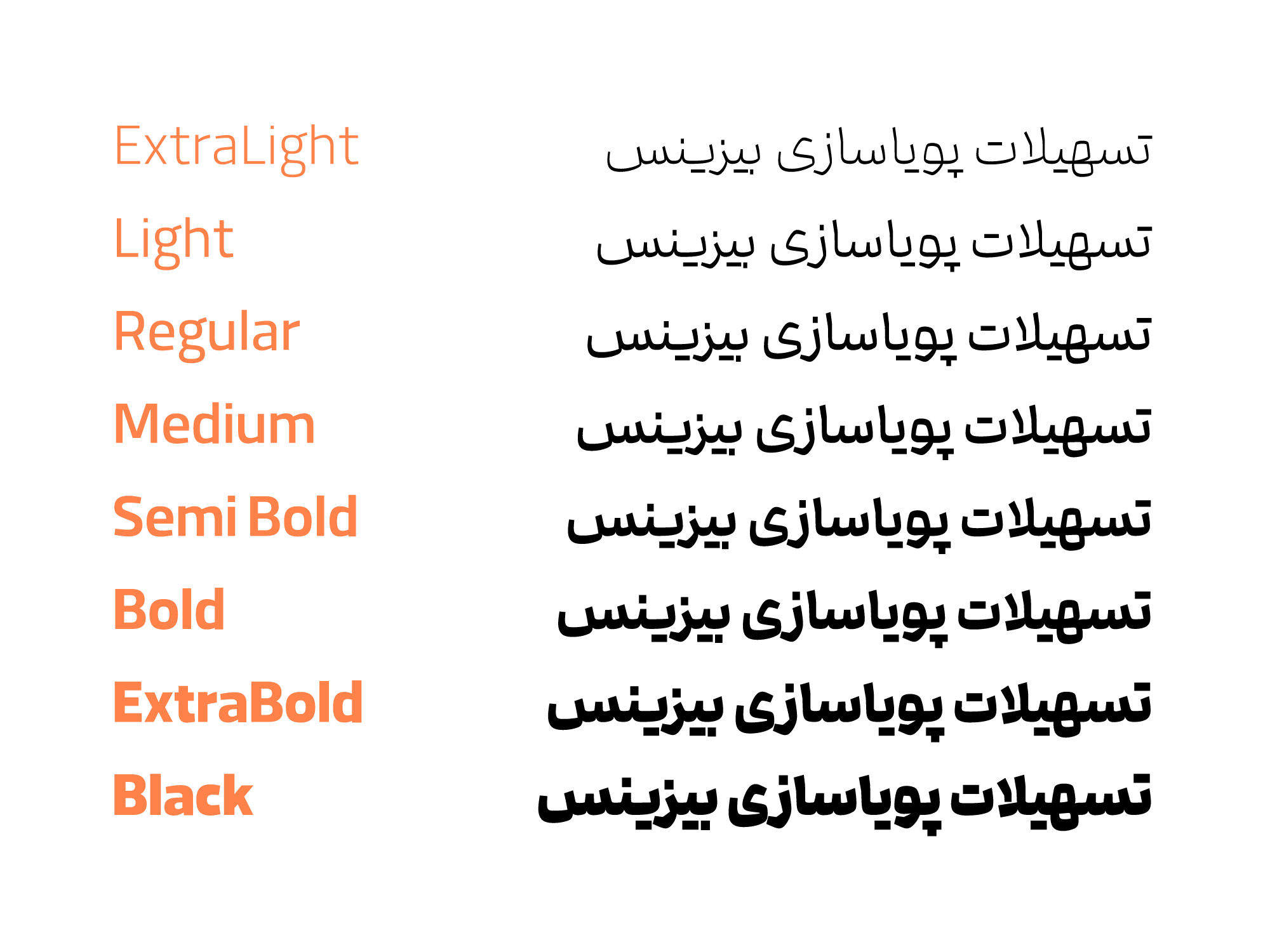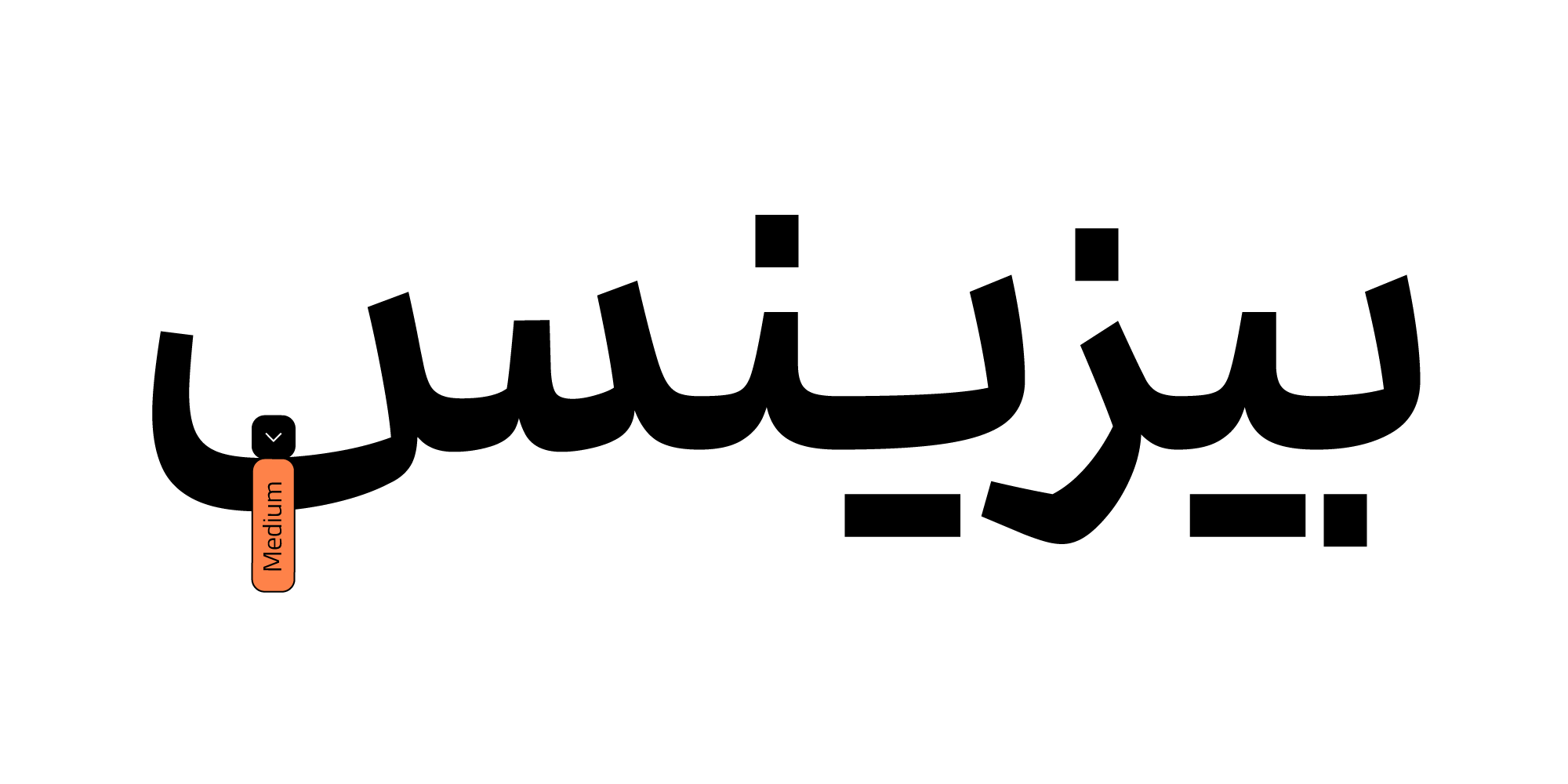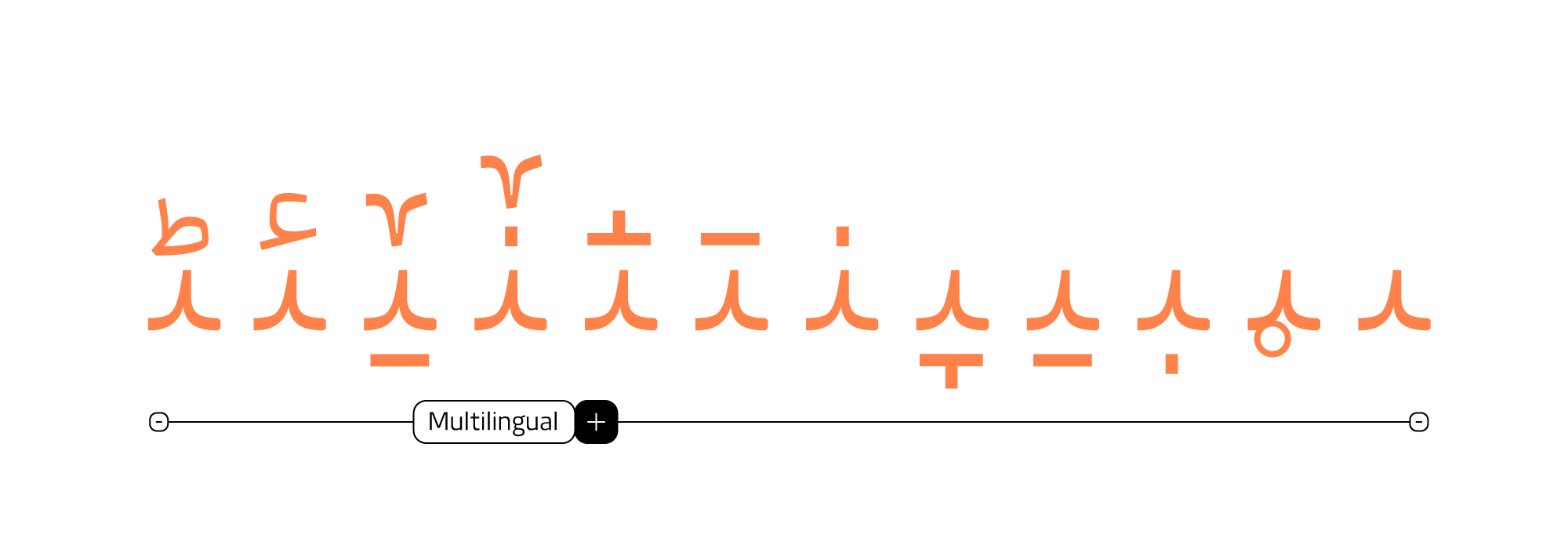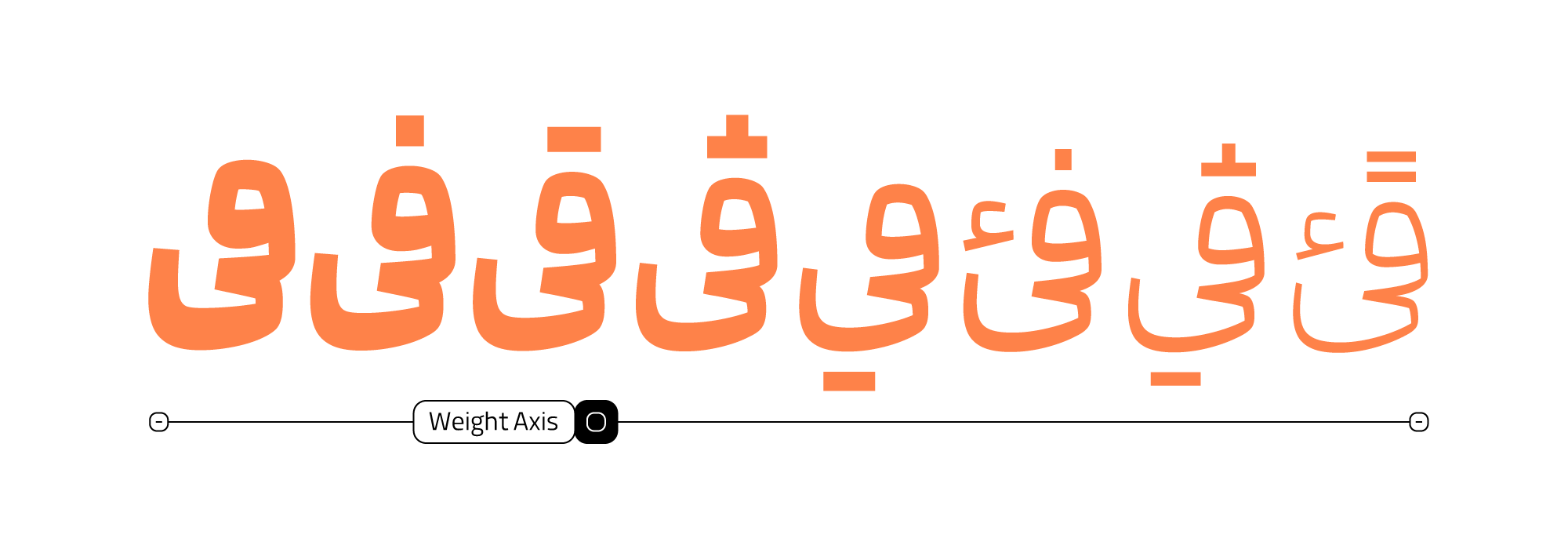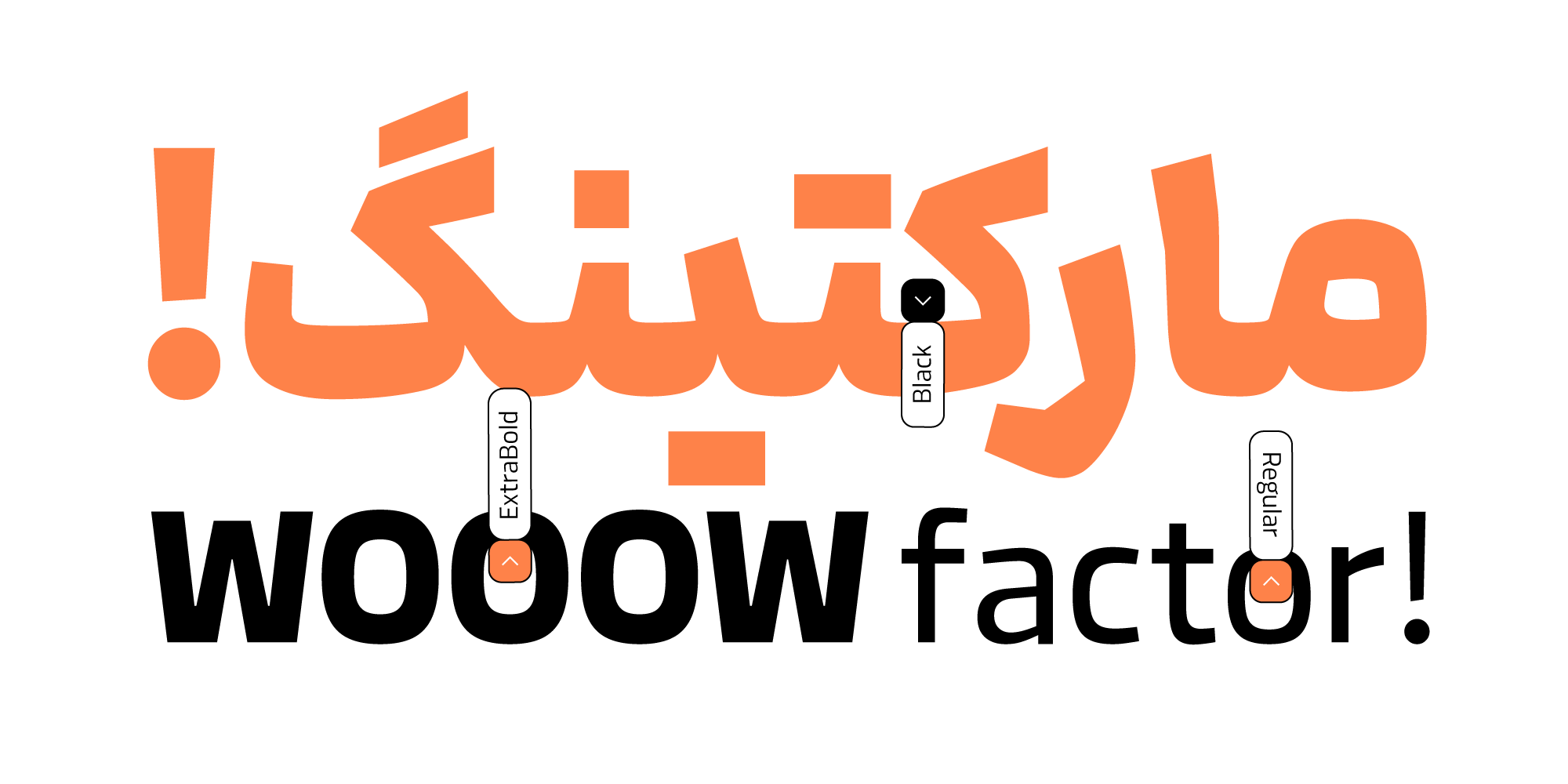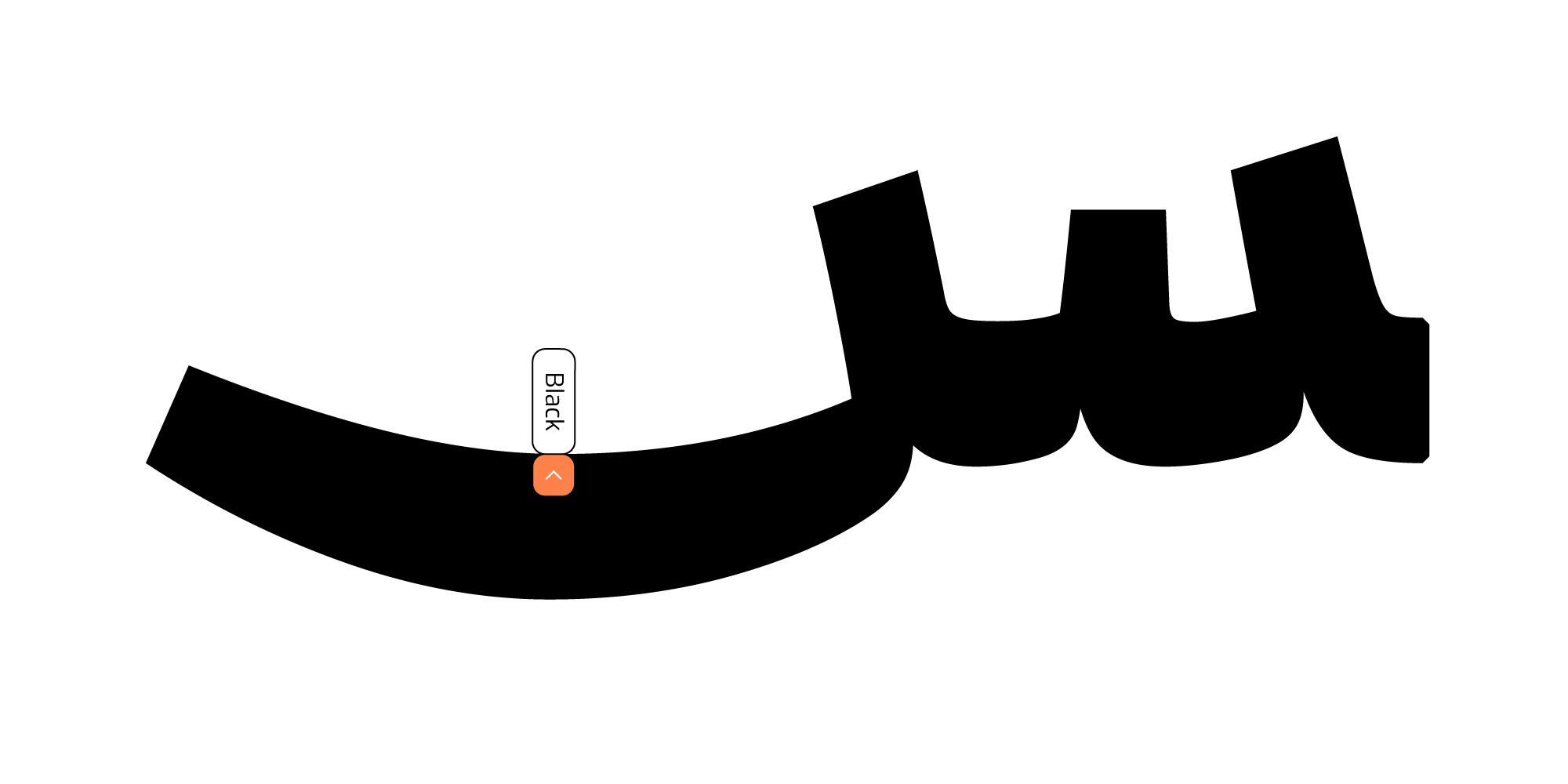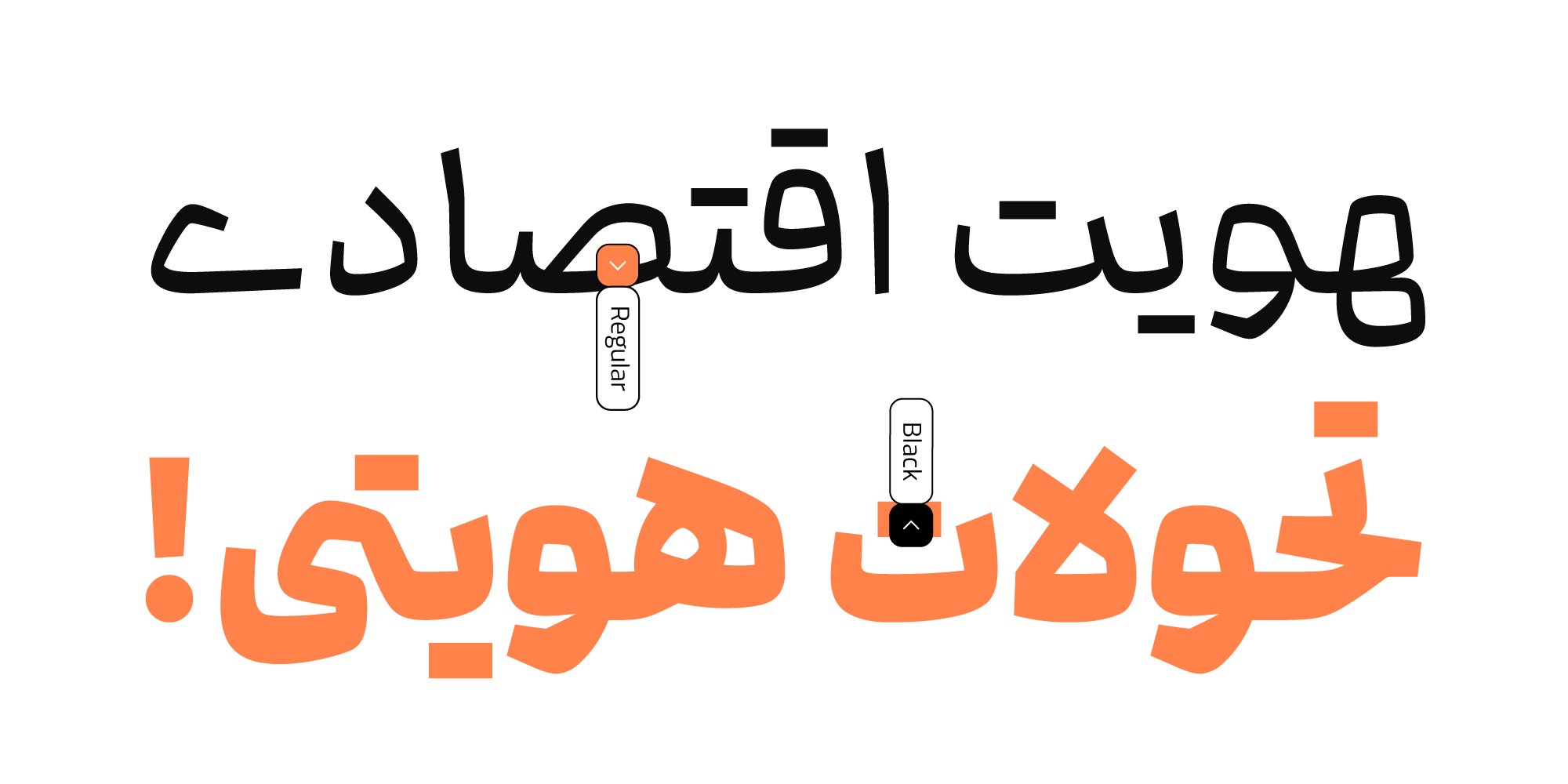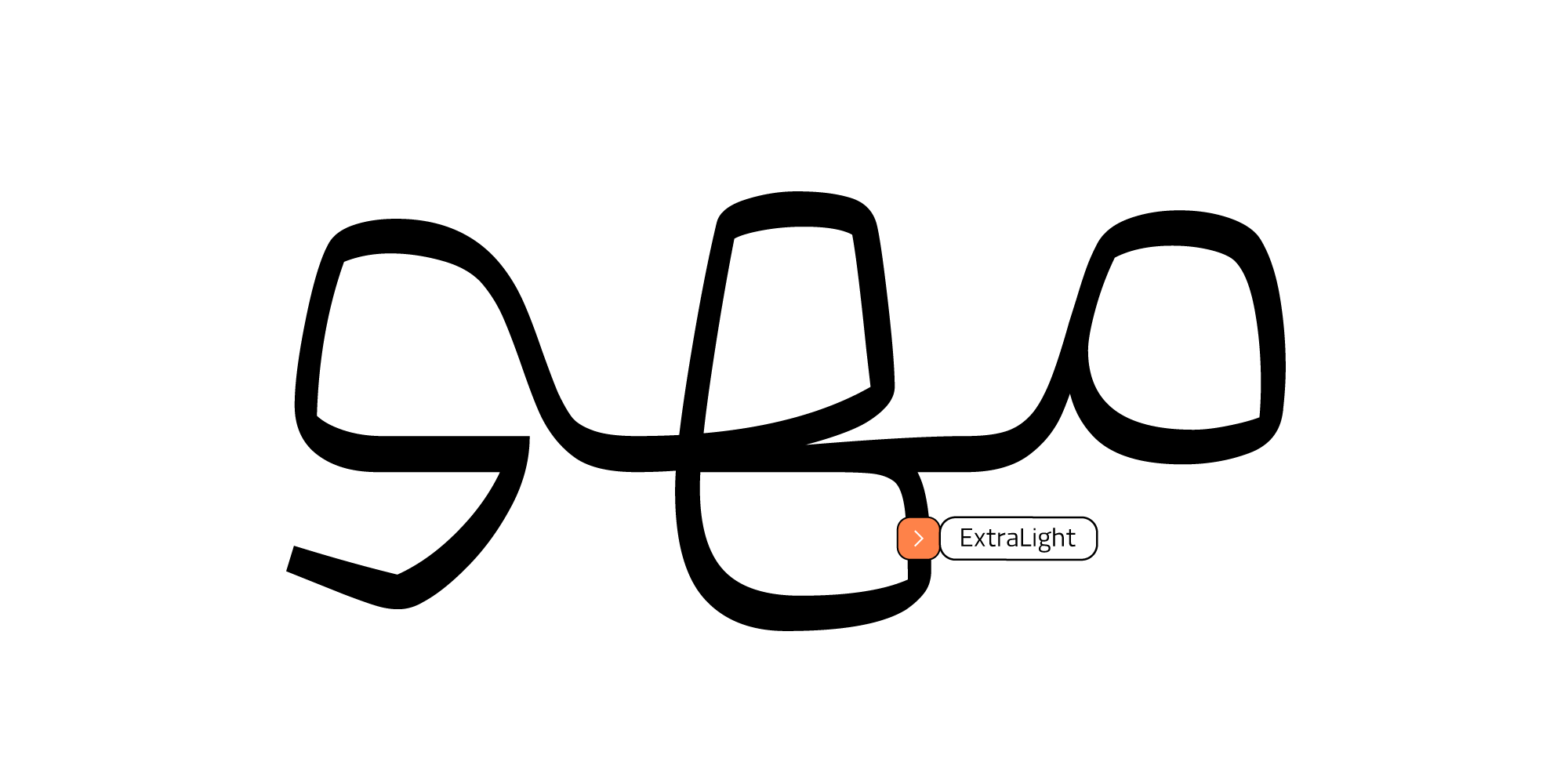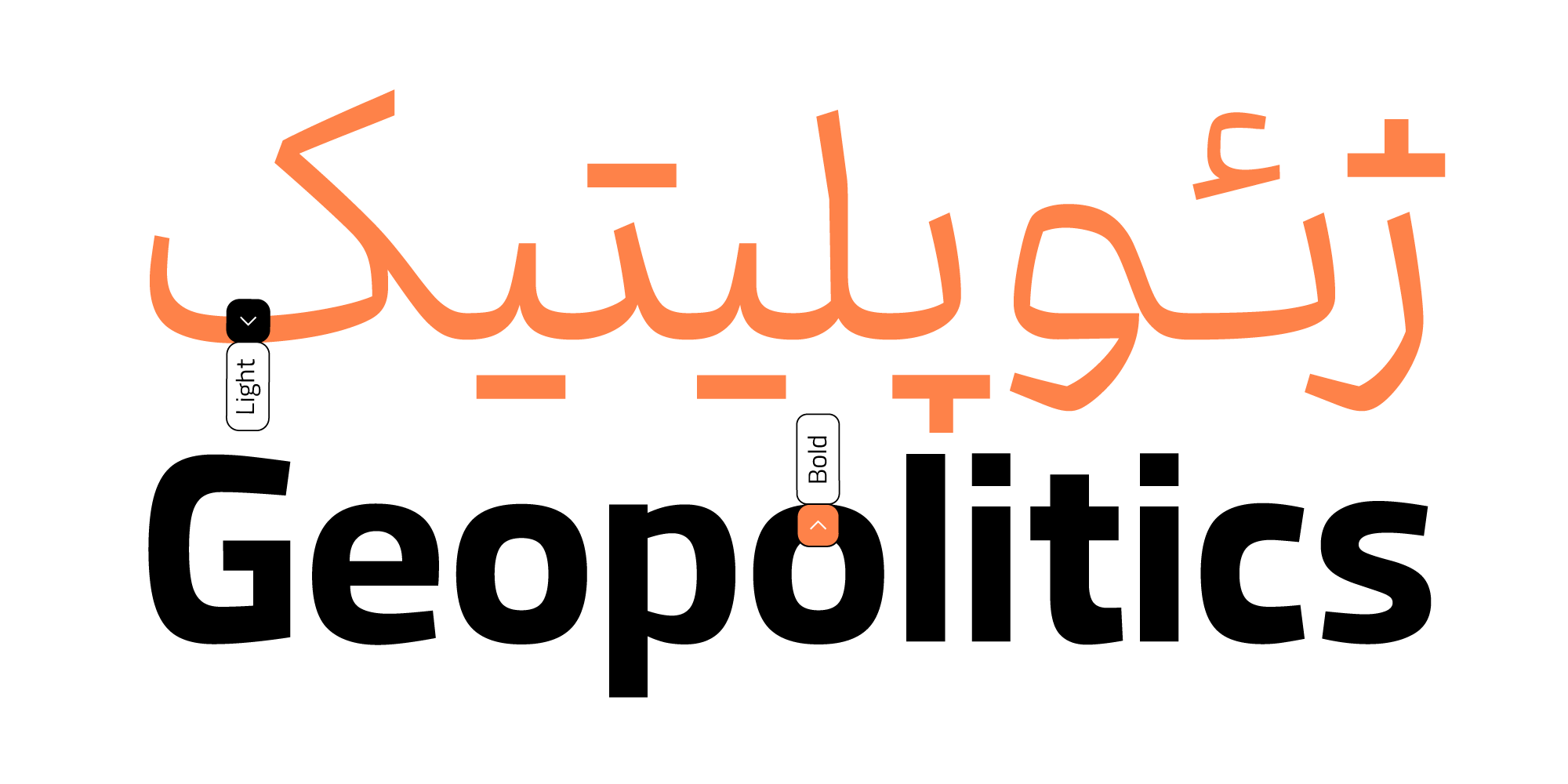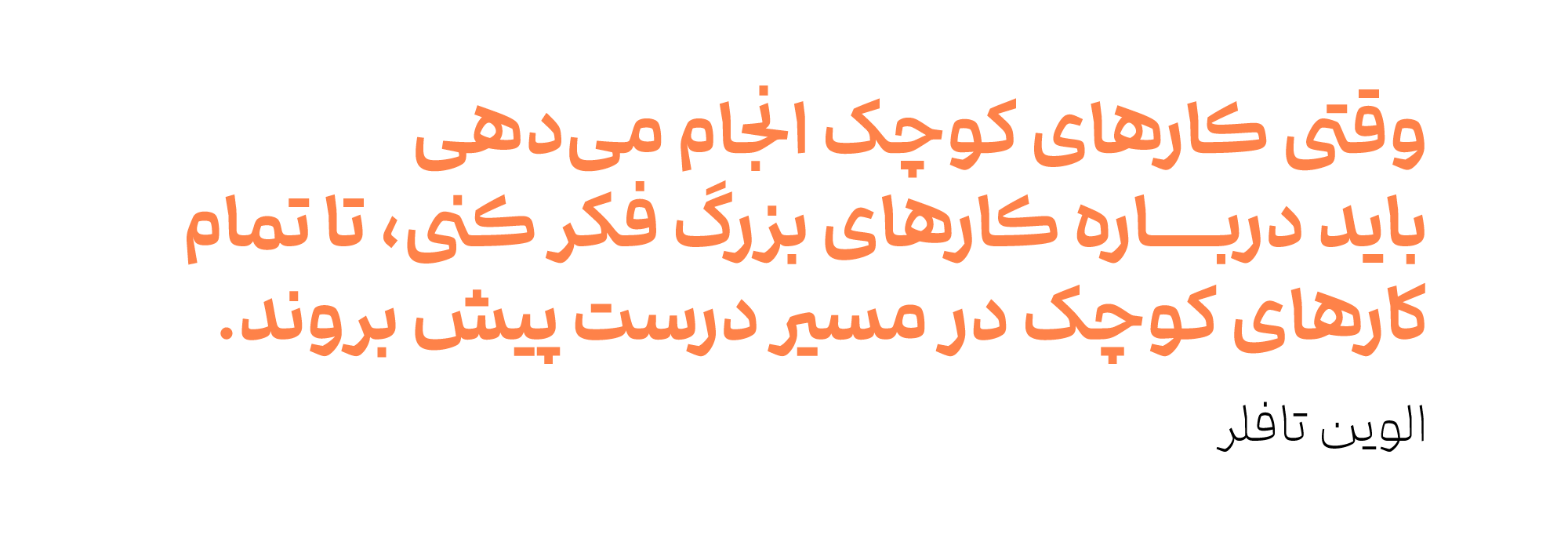
در پی یافتن تناسباتی جدید با حفظ ویژگیهای پایهای رسمالخط فارسی، اولین اتودهای فونت درباره در سال ۱۴۰۱ شکل گرفت. به مرور تناسبات و ویژگیها تغییر یافتند تا اوایل سال ۱۴۰۴ که وزن اکسترالایت کامل شد و سپس مابقی وزنها طراحی شدند.
وریبل فونت
فونت «درباره» به صورت وریبلفونت ارایه شده است که علاوه بر ایجاد دسترسی به وزنهای میانی بین وزنهای استاندارد، تمام وزنها در قالب یک فایل فونت را در دسترس قرار میدهد.
وزنهای استاندارد
«درباره» در بسته حرفهای خود، ۸ وزن استاندارد از ExtraLight تا Black را دارد که این فونت را برای کاربردهای متنوع از تولید محتوی فضای مجازی و UX/UI گرفته تا تبلیغات و چاپ مناسب میسازد. خانواده فونت «درباره» برای استفاده در فضاهای وب نیز بهینهسازی شده است و فایلهای مورد نیاز در کنار فایلهای اصلی قرار داده شده است.
پشتیبانی از زبانهای انگلیسی، عربی، کردی و اردو
تایپفیس «درباره» برای زبان فارسی طراحی شده است و زبانهای عربی، کوردی و اردو و انگلیسی را نیز پشتیبانی میکند. از فونت Cairo برای کاراکترهای لاتین این فونت استفاده شده است.
حروف و ترکیبات جایگزین
برای ایجاد تنوع در شیوه نگارش و خوانایی، جایگزینهایی برای بعضی از حروف و نیز چند ترکیبِ جایگزین دوتایی مشخص شدهاند.
در فونت «درباره» برای تعدادی از حروف، جایگزین طراحی شده است. این حروف جایگزین در دسته Stylistic Alternates قرار دارند که به صورت Stylistic Set (Set01, Set02, Set03) نیز در دسترس هستند.
همچنین حالت کشیده (جایگزین) حرف «ک»، «گ»، «س» وچند حرف دیگر در دسته Swash قرار دارد.
ترکیبهای دوحرفیِ جایگزین که به حرف «ی»، «ر» و «ن» ختم میشوند بهصورت لیگیچرهای Standard Ligatures در دسترس هستند.
همچنین ترکیبهای دوحرفیِ جایگزین که به حرف «ی»، «ر» و «ن» ختم نمیشوند و نمادهای ریال و تومان بهصورت لیگیچرهای Discretionary Ligaturesدر دسترس هستند.
تبدیل اعداد لاتین و عربی به فارسی